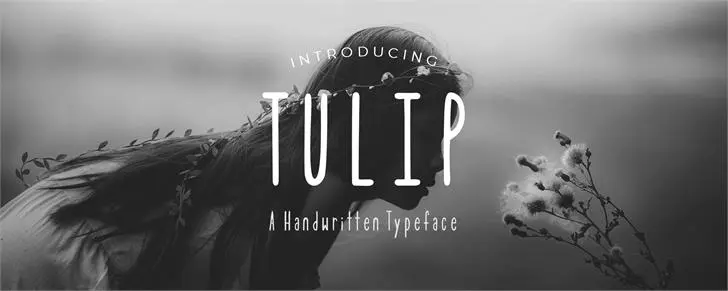
Tulip Font – Download Grátis
A Tulip Font é uma tipografia sans serif elaborada a mão, projetada para ser elegante e versátil, ideal para qualquer projeto. Seu formato alto e fino faz dela um recurso atraente para designers que buscam estilos modernos e distintivos. Esta fonte foi concebida para adaptar-se às necessidades de design variadas, desde pequenos detalhes como títulos e headlines até elementos mais complexos de layout editorial. Com sua versatilidade única, a Tulip Font pode ser utilizada tanto no campo pessoal quanto comercial, uma vez que é gratuitamente disponível para uso pessoal. Os criadores desta fonte oferecem opções de licenciamento comercial em seu site, o www.fonts.creativetwo.us. Sua forma arredondada e acentuada cria um contraste interessante com linhas retas da tipografia tipo sans serif convencional, tornando-a uma opção única para seus projetos visuais.